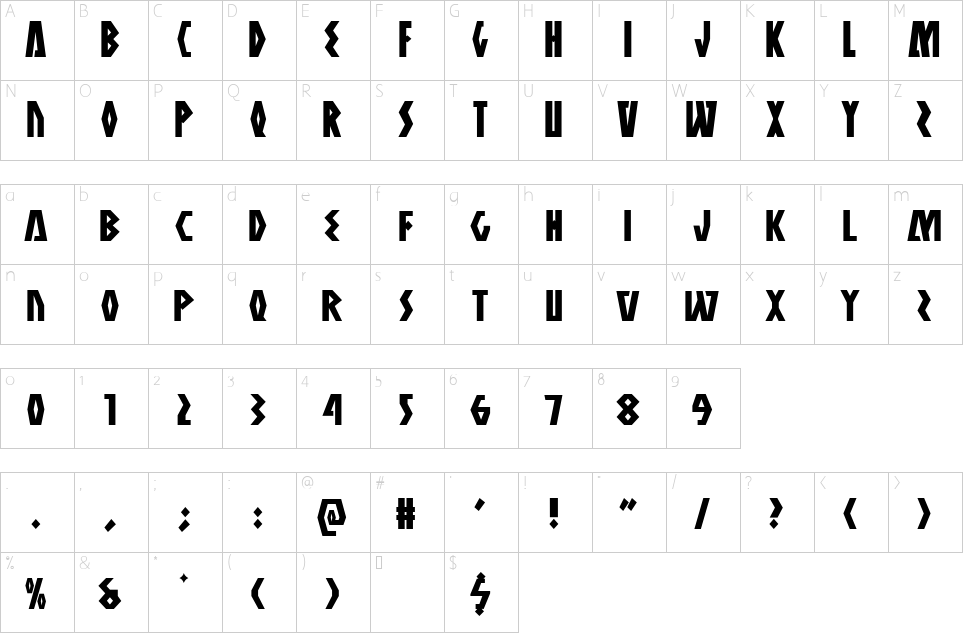
Descubra a elegância e a simplicidade da Antikythera font, uma escolha imperdível para designers e criadores de conteúdo. Desenvolvida pela Iconian Fonts, esta fonte é uma viagem pelo tempo, inspirada no famoso relógio antigo de Antikythera, um artefato tecnologicamente avançado de nosso passado. Com seu design sofisticado e fácil de usar, a Antikythera oferece linhas limpas e uma riqueza de detalhes que combinam perfeitamente com diferentes estilos de design. Disponível tanto para os usuários do Windows quanto para os da Mac, esta fonte grátis é um presente para os amantes de gráficos e criadores de conteúdo que desejam dar um toque único aos seus projetos. Com um design minimalista e versátil, a Antikythera font é uma escolha ideal para criar uma identidade visual única e impactante.